Siempre bendecido
— Siempre bendecido —— Trabalho desenvolvido para meu mano @shaolin_pilacoman , obrigado pela confiança e resistência.
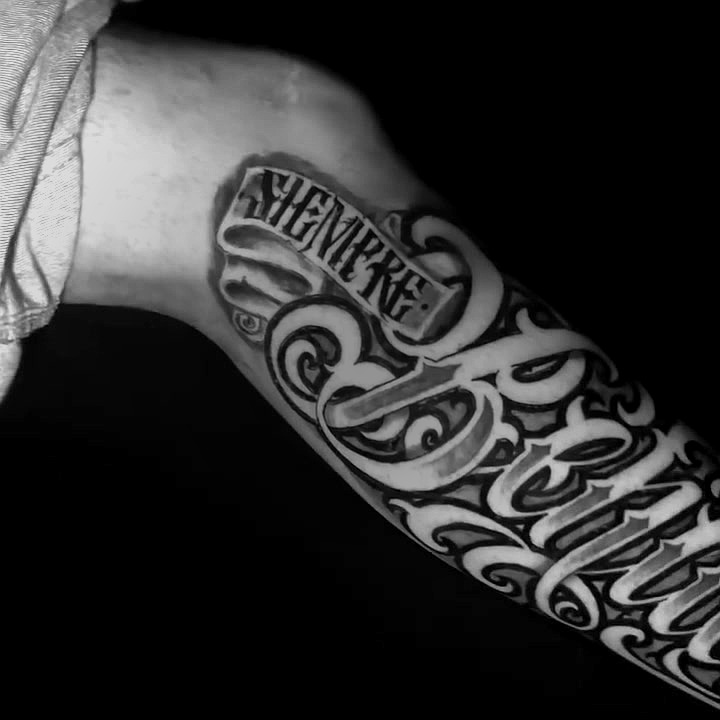
Lettering ornamental · Blackwork · Peça autoral · Flash
— Siempre bendecido —— Trabalho desenvolvido para meu mano @shaolin_pilacoman , obrigado pela confiança e resistência.
-— Perdão e gratidão —— Trabalho desenvolvido para meu mano @perk.vns Obrigado pela confiança e pela resistência👊🙏 #letteringtattoo #tattooartist #script #guarulhostattoo
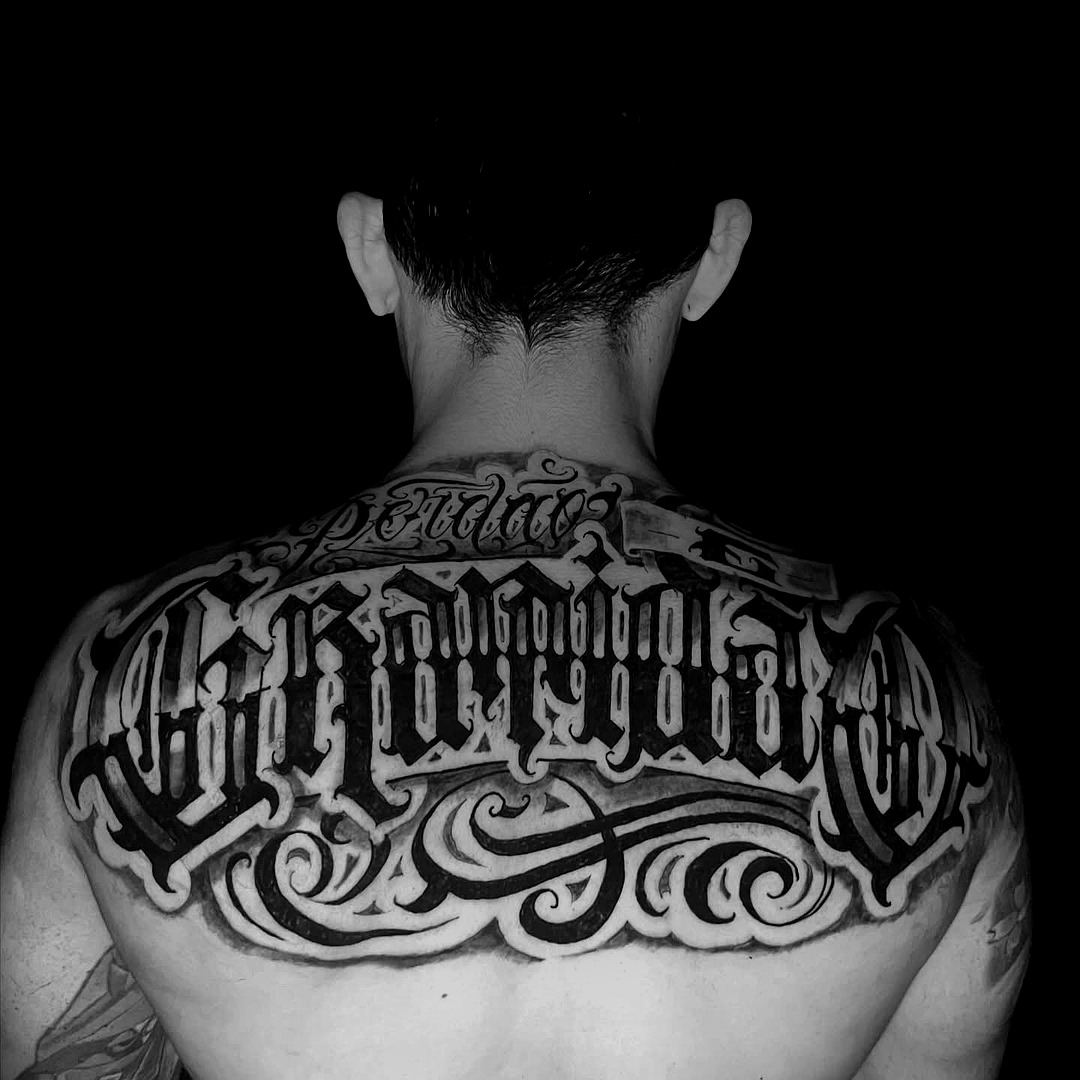
—- Essência—- Trabalho desenvolvido para a @1s4.__ . Agradeço pela confiança e obrigado a todos que acompanham meu corre🙏🏻🚀
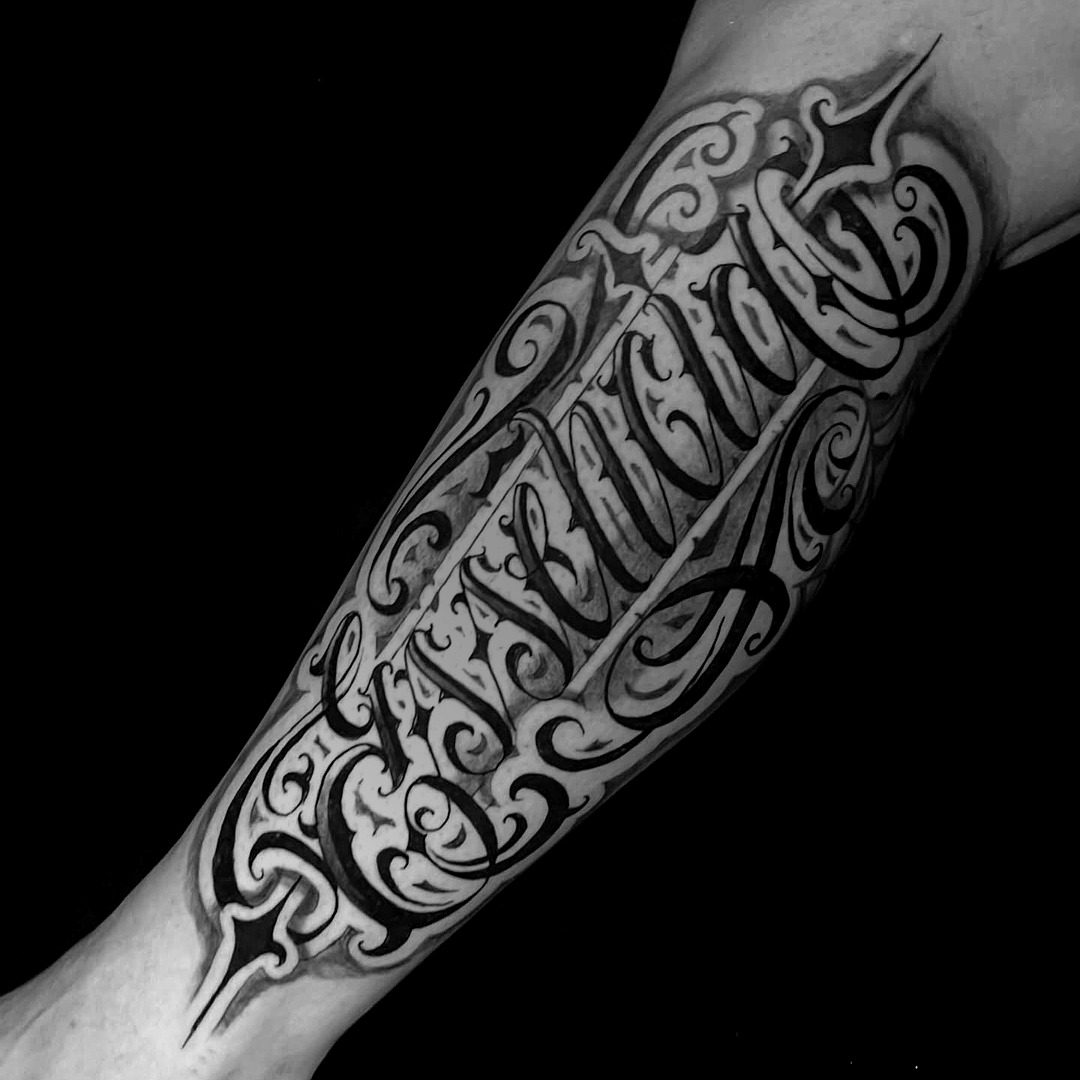
Trabalho realizado na Carol. Obrigado pela confiança e resistência.🙏🏻👊 #tattoo #blackandgray #grutattoo #grucity #tattooed
—- Elisa —— Trampo realizado no meu irmão em homenagem à sua filha Elisa. Tamo junto, mano, obrigado pela confiança.🙏🏻 #script #gru #customlettering #letras #lettering
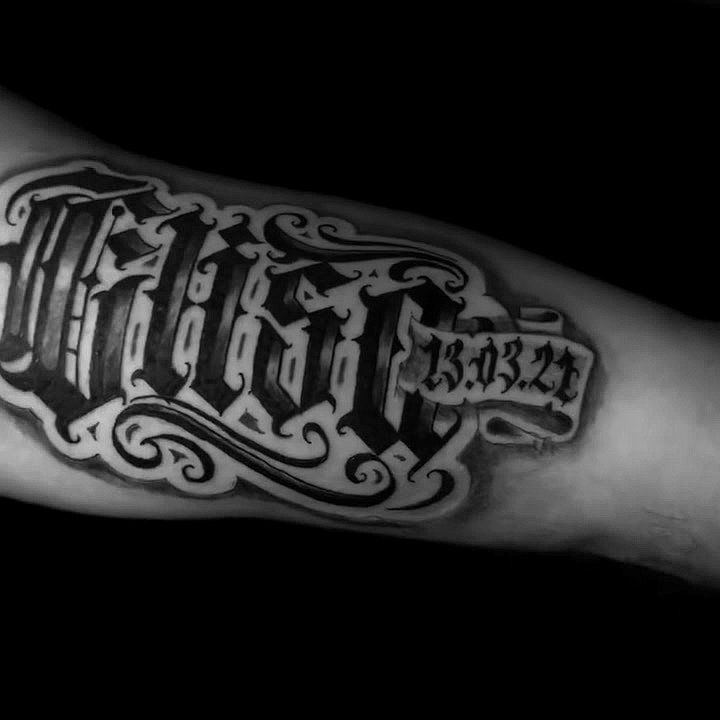
— Seu único limite é a mente — Trabalho autoral desenvolvido para @tekahreal Agradeço a confiança e obrigado a todos que acompanham meu corre. #script #customlettering #letras #gru
—— CITY RUNNERS —— Frase inspirada no som do @zusflee e do @kyanmaloka Feito no meu mano @isaac_alv3s agradeço a confiança e a resistência. Tmj!🙏🚀🚀 #script #customlettering #grutattoo
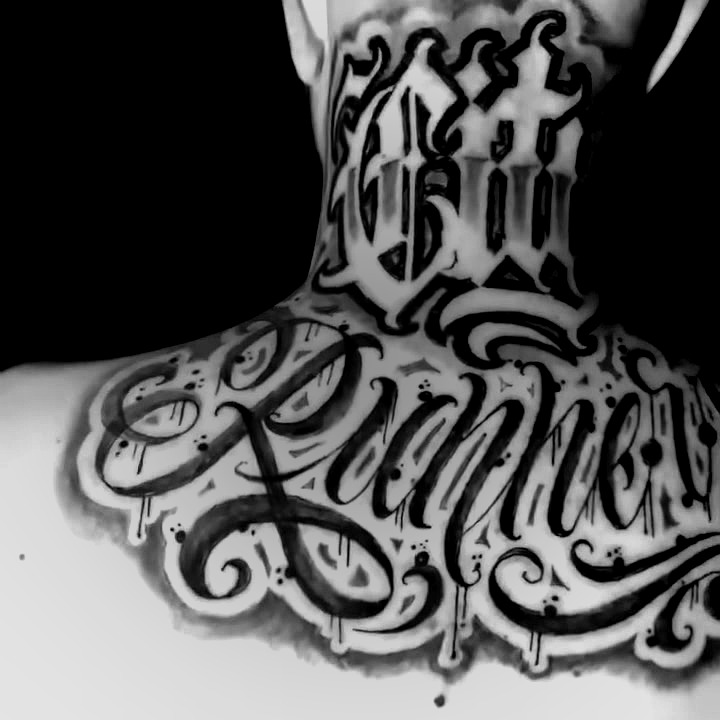
— Que o dinheiro nunca compre sua postura — Trabalho autoral desenvolvido para Luana Agradeço a confiança e obrigado a todos que acompanham meu corre.🙌🚀
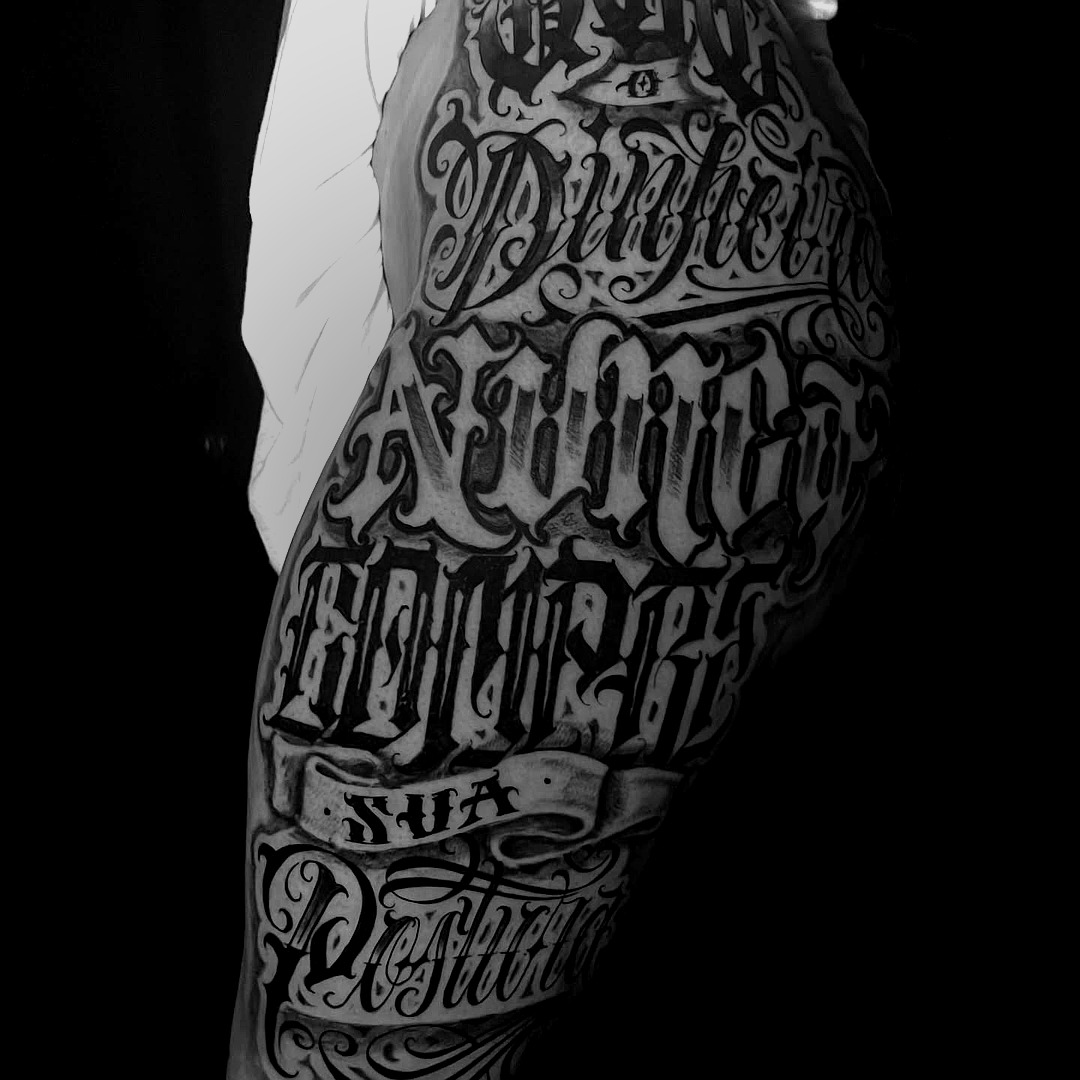
Trabalho que rolou no meu mano @laurostreet Agradeço a confiança, meu mano 🙏
— Autêntica — Trabalho desenvolvido para Ana Obrigado pela confiança e resistência. 🙏🙌 #letras #script #customlettering #tattoo
— SE DEUS QUISER E ELE HÁ DE QUERER! COM DEUS TUDO SE AJEITA. TE AMO FILHO! MUITO, MUITO, MUITO. UM BEIJO — Trabalho realizado para meu mano @caio.ricardo_ em homenagem a sua avó. Obrigado pela confiança e paciência. 👊🚀
— RITMO E POESIA — Trabalho autoral desenvolvido para meu mano @cp.ludico 👊 Agradeço a confiança e obrigado a todos que acompanham meu corre. 🙏🏻🚀 #customlettering #letteringtattoo #script #guarulhostattoo #gru #tattoo
C/S consafos, para meu mano @sebatattooer . Tmj monstro🙏🏻🔥
Trabalho que rolou no meu mano @vulgosincero Agradeço a confiança, meu mano 🙏🏻
— Resilience — Trabalho autoral desenvolvido para meu mano @salvedu_____ 👊🏻 Agradeço a confiança e obrigado a todos que acompanham meu corre. 🙏🏻🚀
— PERDÃO/GRATIDÃO — Trabalho realizado para amiga @tthaistattoo Obrigado pela confiança. 🙏🏻 #script #guarulhostattoo #lettering #letteringtattoo
— UNSHAKABLE — Trabalho desenvolvido para @laribolsoni Obrigado pela confiança e agradeço todos que acompanham meu corre. 🙏🏻
Trabalho que rolou no meu mano @cp.ludico Agradeço a confiança, meu mano!🙏🏻
- FreeStyle - Trabalho realizado para meu mano @doestera obrigado pela confiança 🙏🏻 brow
- Clareza na ideia, pureza no coração - Trabalho autoral realizado em uma sessão, obrigado @gc_mamacita pela confiança e paciência 🙏🏻
- Chora Agora, Ri Depois - Trabalho feito no meu mano @isaac_alv3s agradeço pela confiança mais uma vez
-Skate por Amor - Tattoo feita no meu mano @rubronsons Tmj meu parceiro 🙏 #tattoo #lettering #lettetingtattoo #guarulhostattoo #011
-Trust no One- Desenvolvido para @thsholanda obrigado pela confiança e liberdade de criação 🙏 #letras #guarulhostattoo #letteringtattoo
-- Viva livre ou morra -- Trabalho autoral desenvolvido para o @vulgosincero obrigado pela confiança mais uma vez meu mano🙏🚀 #letras #script #customlettering #customletters #guarulhostattoo #tattooart